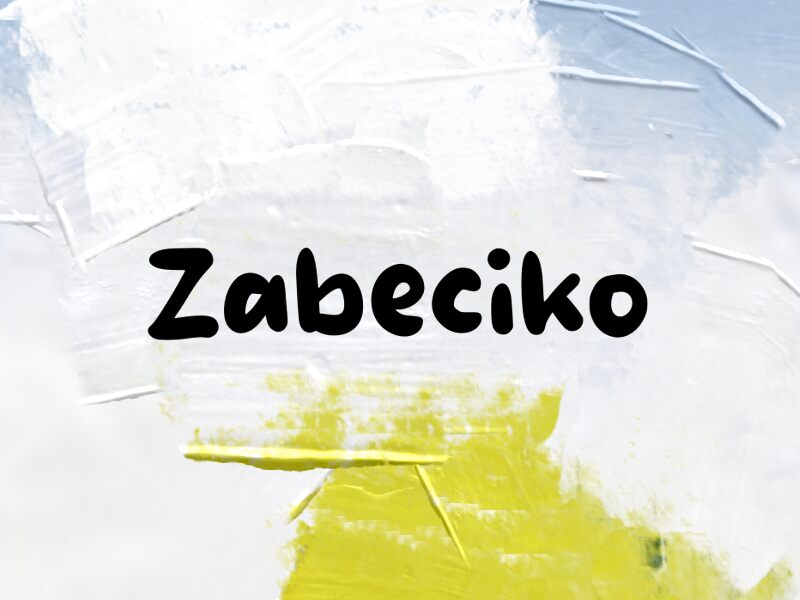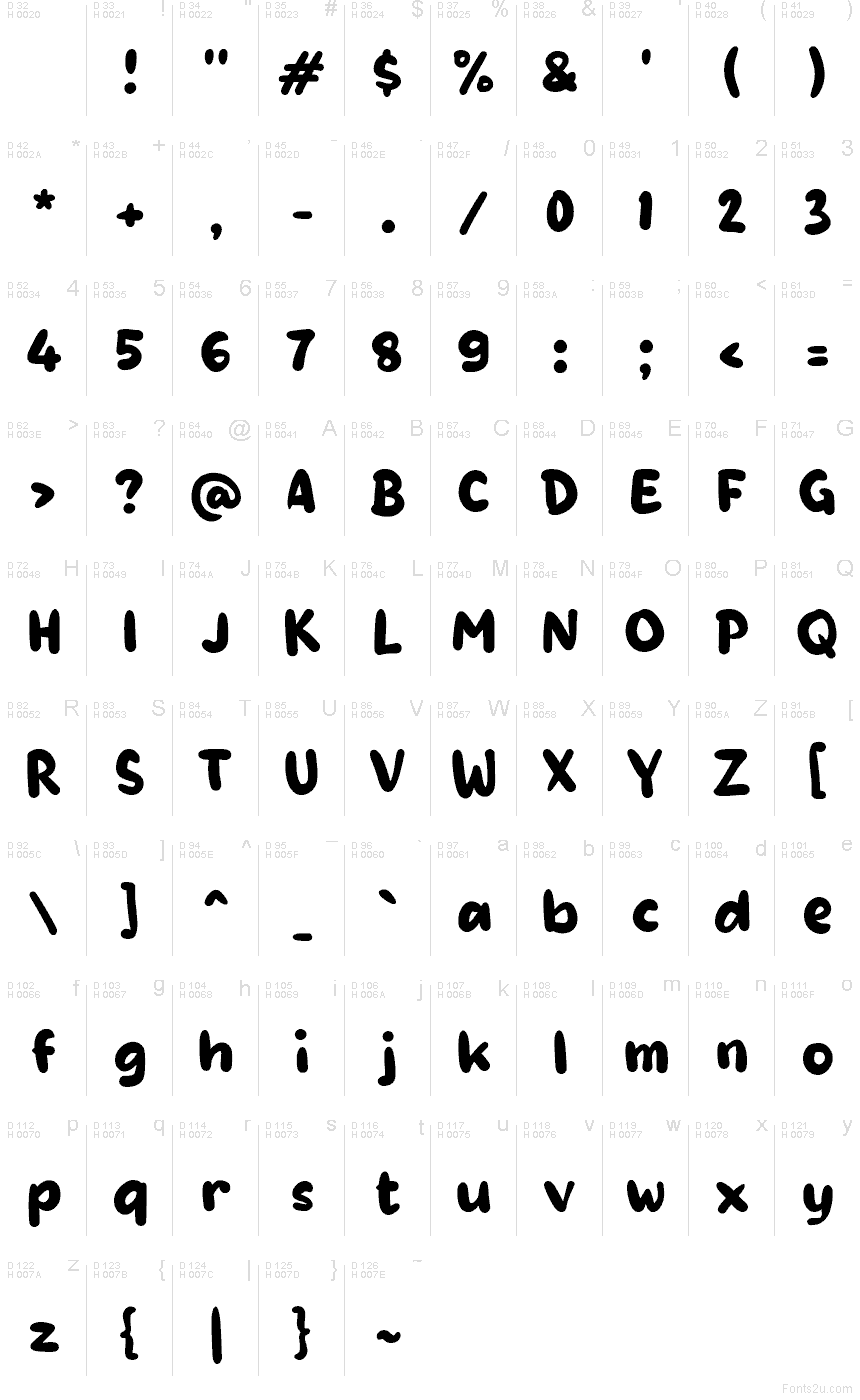
Zabeciko
Zabeciko od Wep je bezplatné komiksové display písmo definované mäkkou, nafúknutou siluetou, vďaka ktorej písmená vyzerajú, akoby boli vyliate a nie kreslené. Široké zaoblené tvary a mierne asymetrický rytmus mu dodávajú živý a neformálny ráz, zatiaľ čo nepravidelná horná línia zabraňuje tomu, aby pôsobilo príliš uhladene alebo geometricky.
Táto nadýchaná hmota dodáva krátkym nadpisom na detských plagátoch, obaloch pochutín, školských materiáloch, pozvánkach na párty či bežnej sociálnej grafike priateľský nádych. Skvele funguje aj pri dizajne nálepiek a miniatúrach pre YouTube, kde oblé tvary udržiavajú veľké nápisy živé bez toho, aby sa písmo stalo len jednorazovým vtipom.